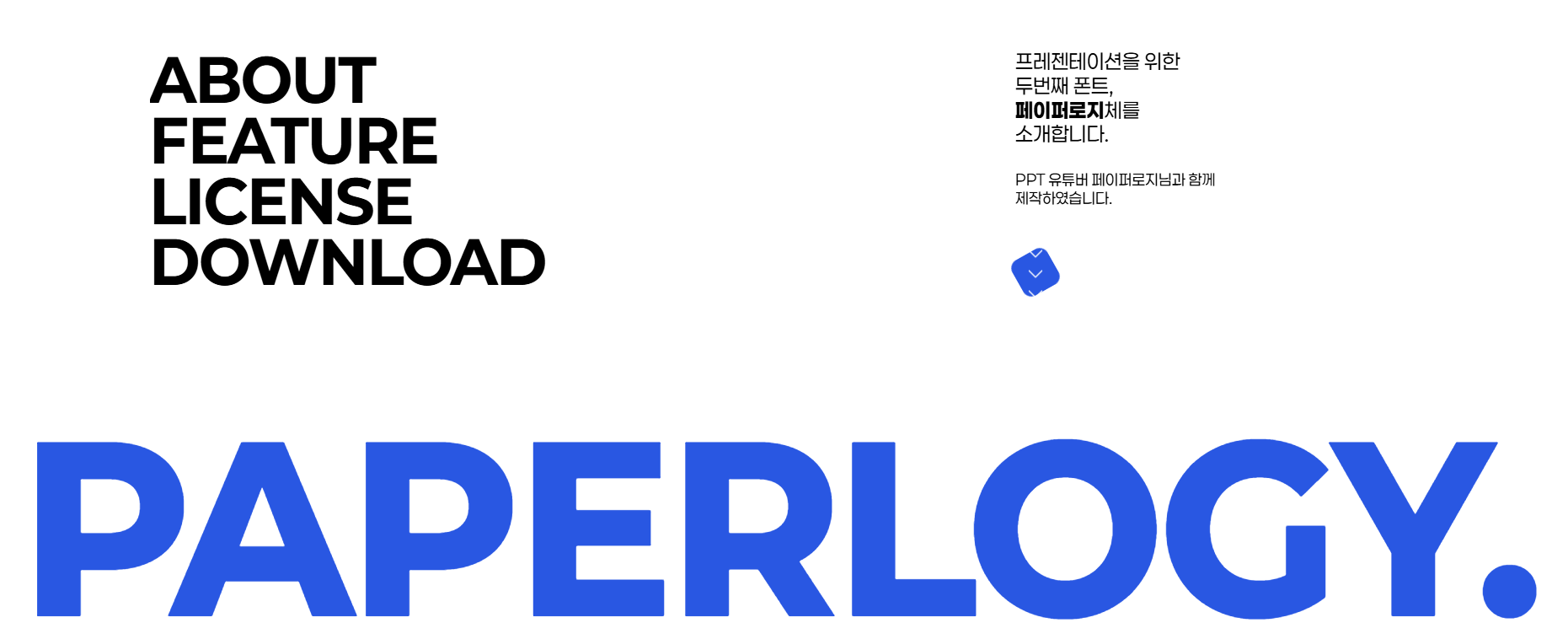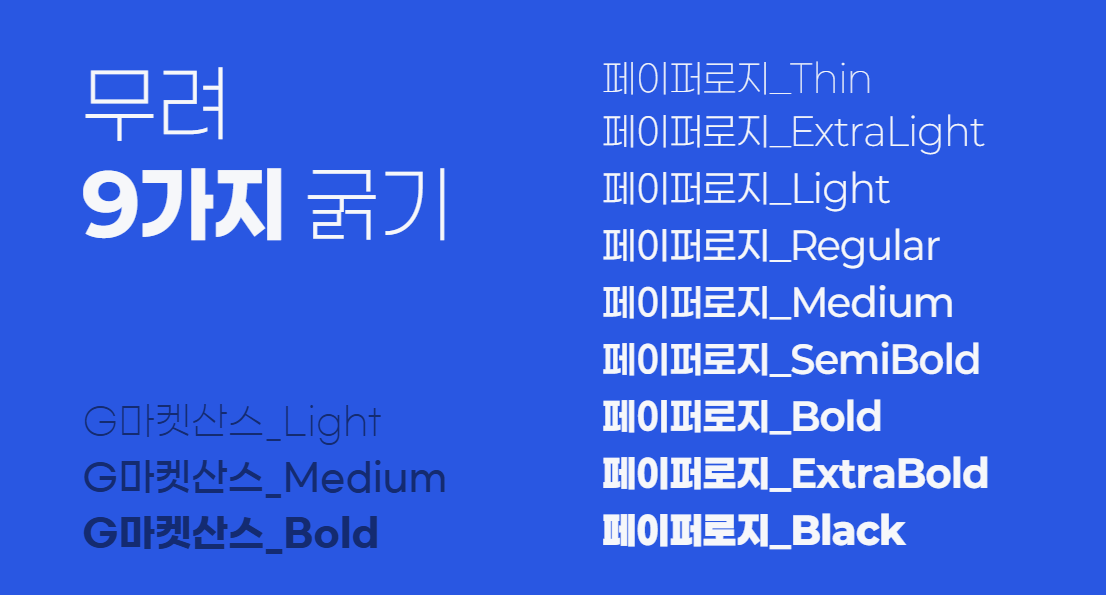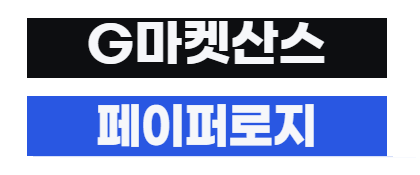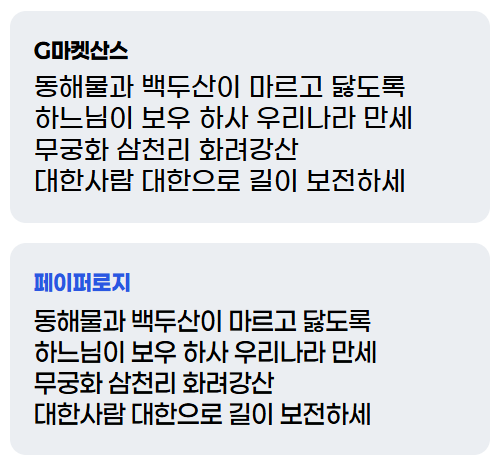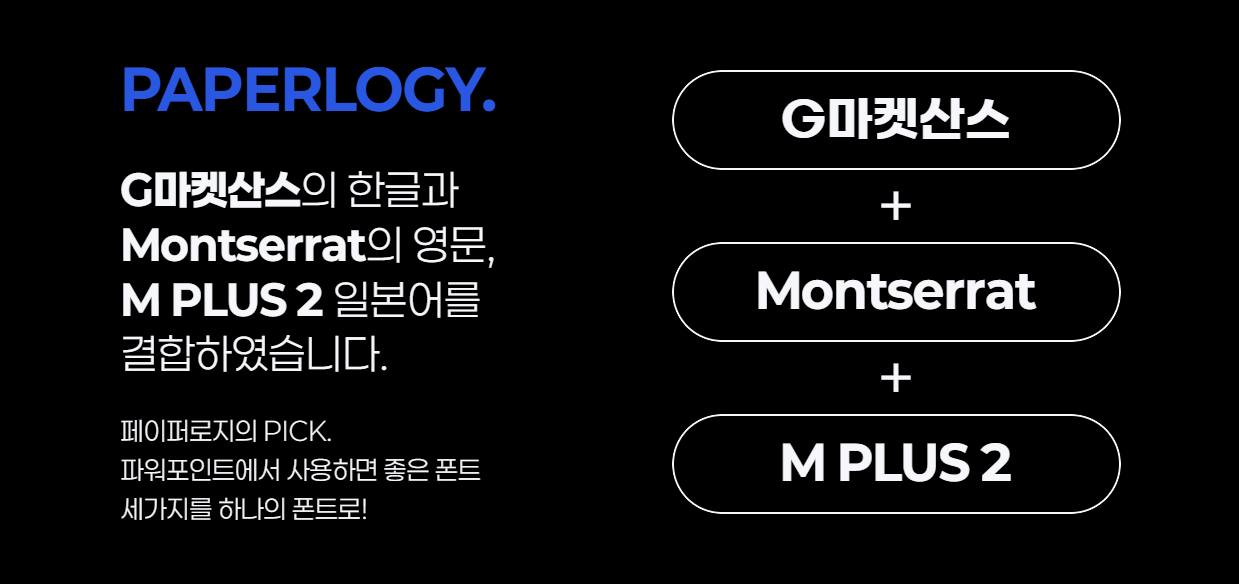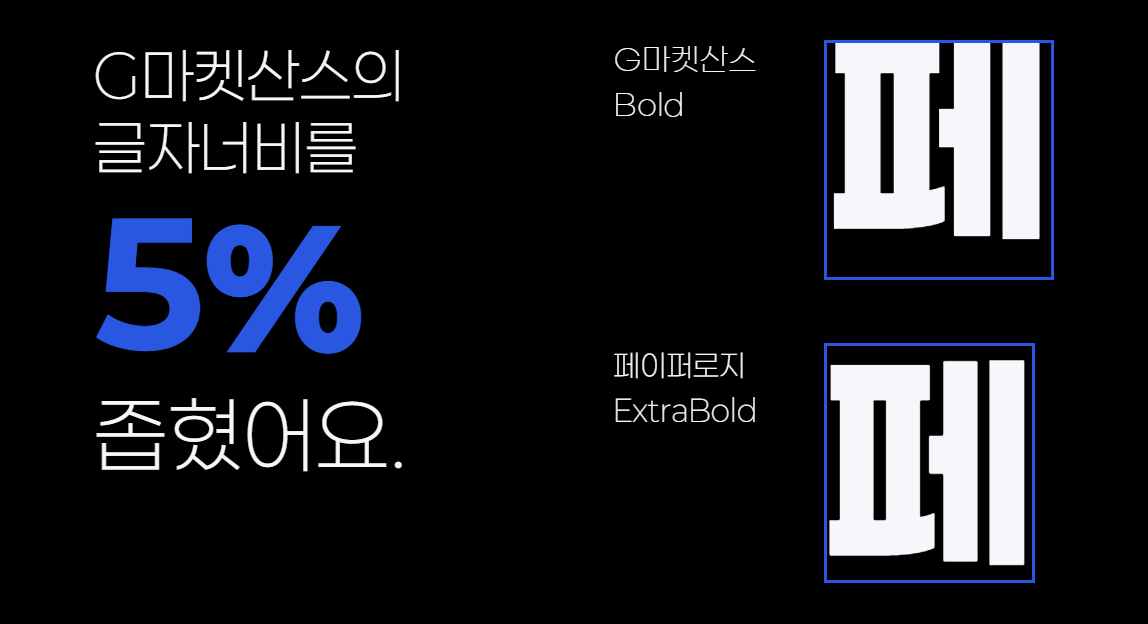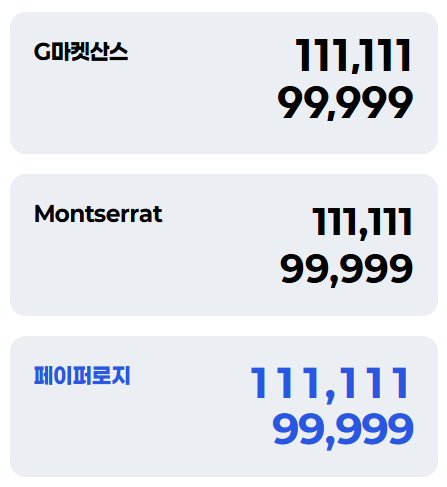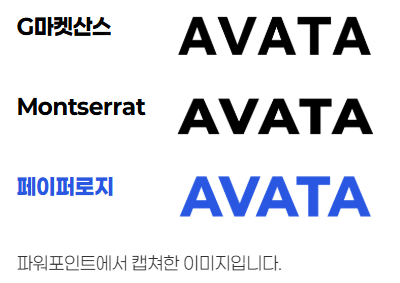
지난번 프리젠테이션에 특화된 폰트로 "프리젠테이션(Freesentation)" 폰트를 소개한 적이 있었는데 이어서 2번째 추천 폰트인 "페이퍼로지(Paperlogy)" 폰트를 소개해 보려고 합니다.
지난번 프리젠테이션 폰트와 마찬가지로 이주임 디자이너가 제작해 주신 폰트로 프리젠테이션 유튜버로 유명한 페이퍼로지님과 협업하여 제작하신 폰트라고 합니다.
이번 페이퍼로지 폰트는 페이퍼로지님이 선택한 파워포인트에서 사용하면 좋은 폰트 세가지로, G마켓산스의 한글과 Montserrat의 영문, M PLUS2 일본어를 결합하여 제작되었습니다.
프리젠테이션 폰트와 페이퍼로지 폰트의 기본이 된 베이스 폰트의 차이를 잠시 알아보겠습니다.
구분 | 페이퍼로지 | 프리젠테이션 |
한글 베이스 | G마켓산스 | 본고딕(Noto Sans) |
라틴 베이스 | Montserrat | Roboto |
한자(일본어) 베이스 | M Plus2 | 본고딕(Noto Sans) |
페이퍼로지 폰트는 G마켓산스와 다르게 총 9가지 굵기로 제작되어 상황에 따라 좀 더 다양한 굵기의 폰트로 강조 및 꾸밈을 진행할 수 있습니다. 또한 글자의 너비도 G마켓산스 대비 5%정도 좁혀서 제작되었습니다.
이번 페이퍼로지 폰트의 특징 몇 가지를 확인해 보겠습니다.
1. 읽기전용 폰트 아니고, 수정 가능한 폰트
2. 글자와 도형 높이 중심 맞춤
G마켓산스가 윗쪽으로 쏠려서 여백 조정하느라 귀찮으셨죠? 페이퍼로지체는 도형 중심에 딱 맞춰 정렬됩니다.
3. 윈도우에서도 텍스트 투명 윤곽선이 필요 없어요.
윈도우에서 G마켓산스가 거칠게 나와서 일일이 텍스트에 투명 윤곽선 넣느라 많이 불편하셨죠? 페이퍼로지체는 그냥 써도 깔끔!
4. 파워포인트에서 커닝 잘 적용됩니다.
많은 폰트들이 파워포인트에서 적이이 적용되지 않습니다. G마켓산스나 Monserrat도.. 그렇지만 페이퍼로지체는 커닝까지 완벽!!
5. 자간 조정없이 그대로 사용하세요.
자간 조정이 필요 없도록 기본 자간을 좁혀두었습니다.
6. 한 눈에 수치 비교가 가능한 고정폭 숫자!
모든 숫자의 너비를 동일하게 하였습니다.
프리젠테이션 작업이나 기타 디자인 작업들에 활용하기 좋은 폰트이니 사용해 보시길 추천합니다.